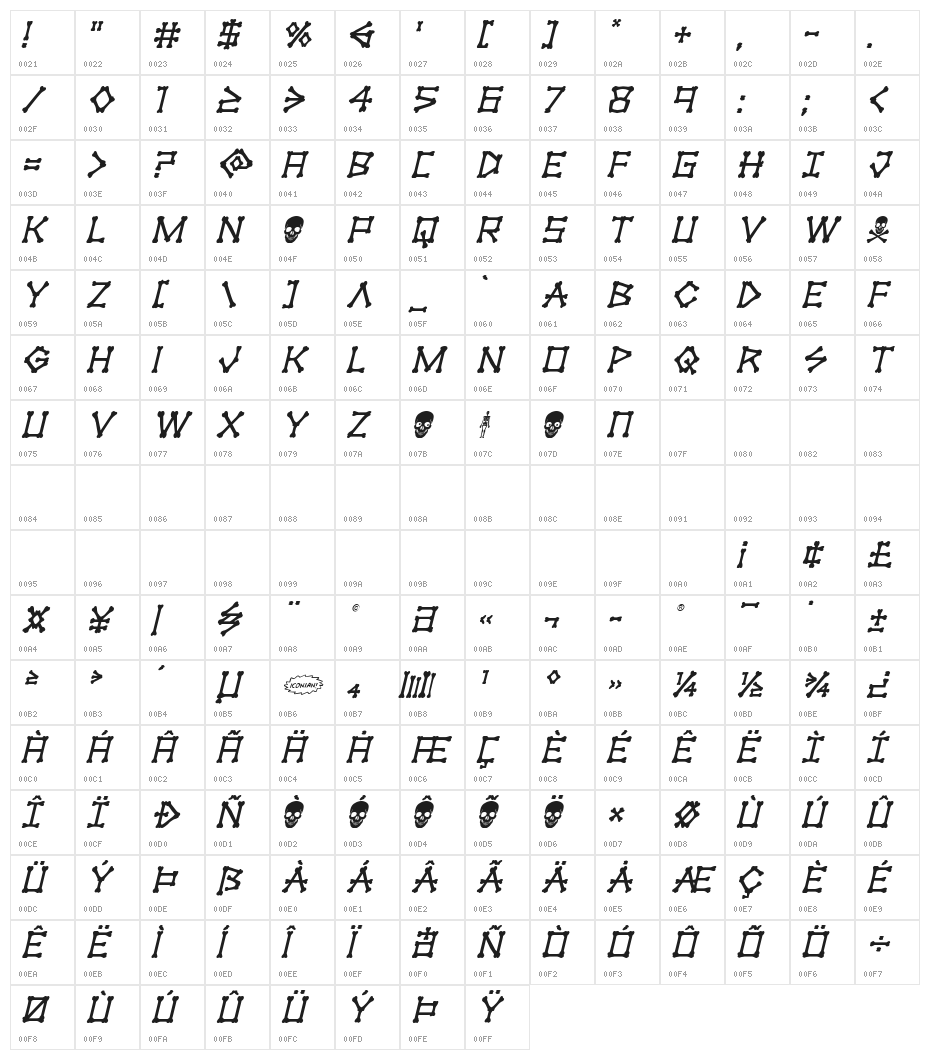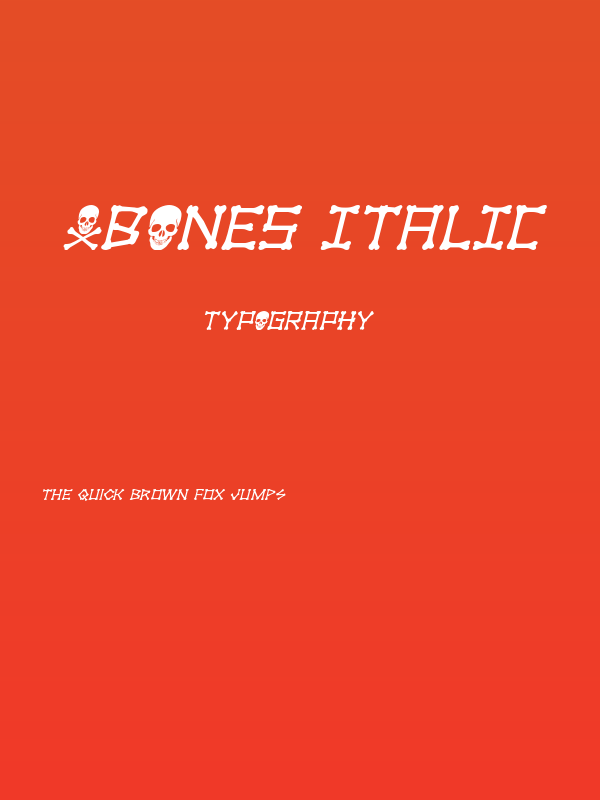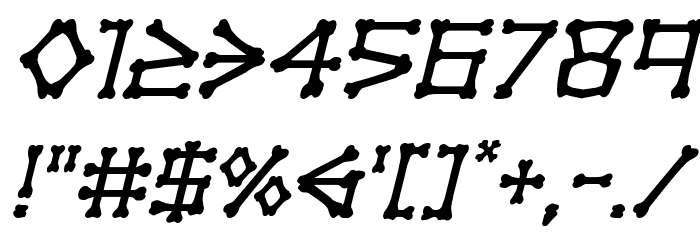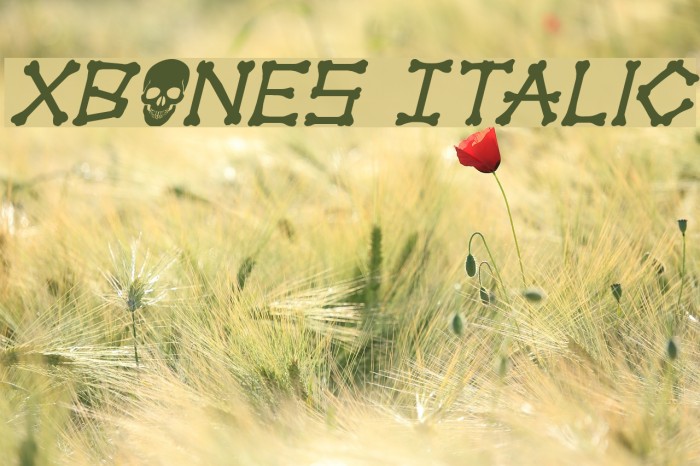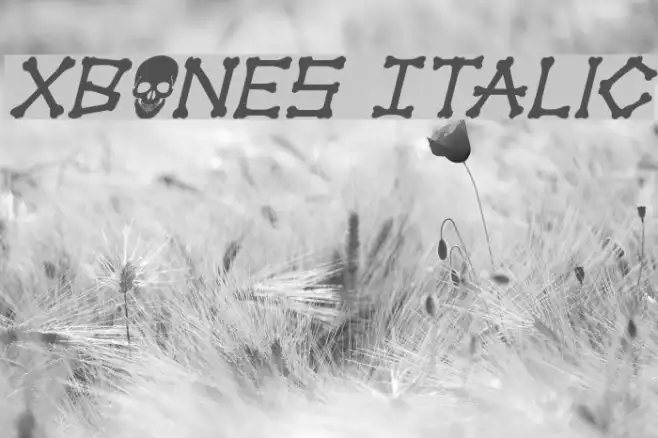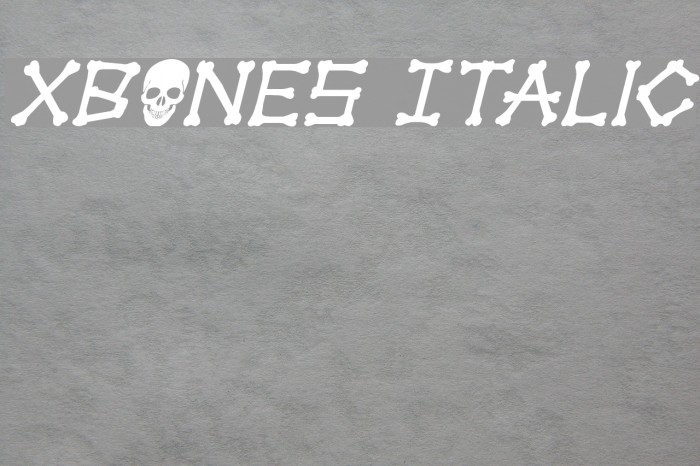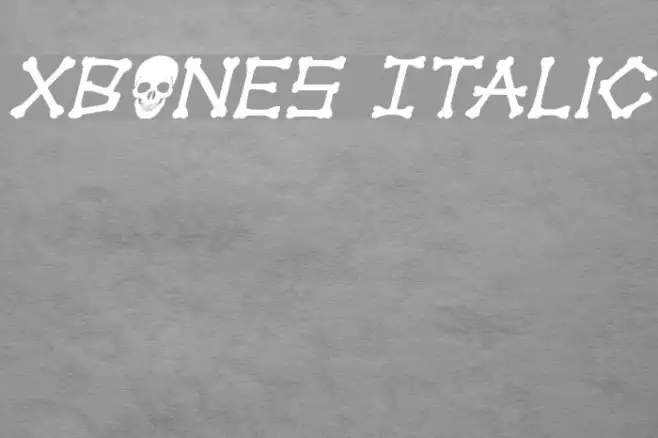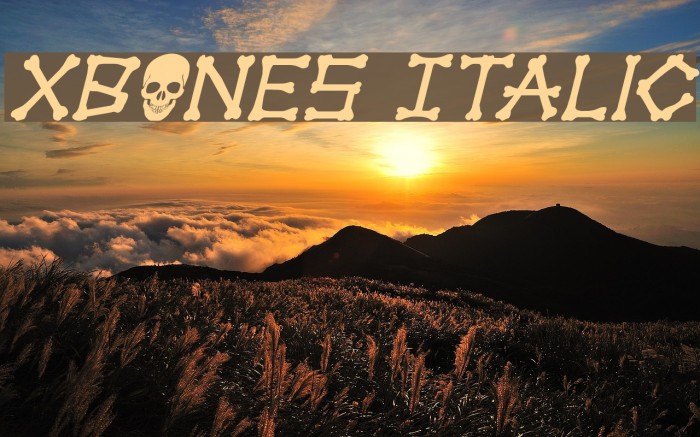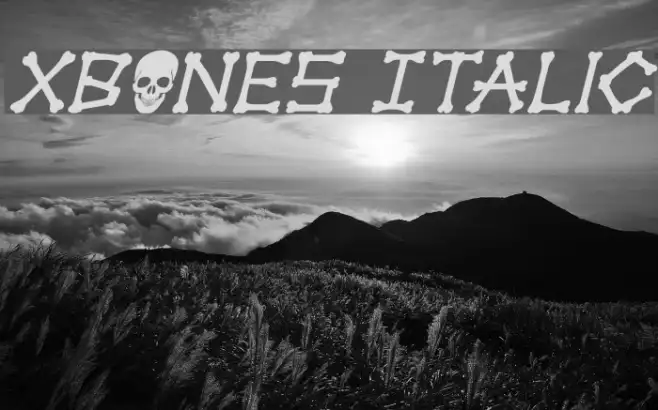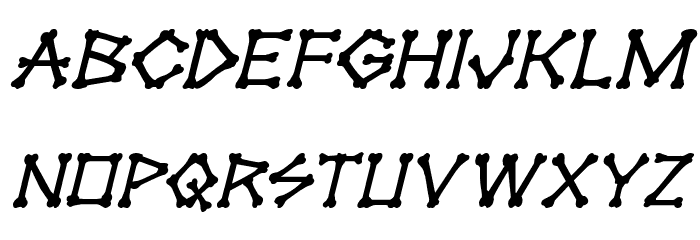
xBONES Italic Font
| Proyectos propuestos | Ideal for Halloween-themed posters, horror movie titles, spooky event invitations, and adventurous branding. |